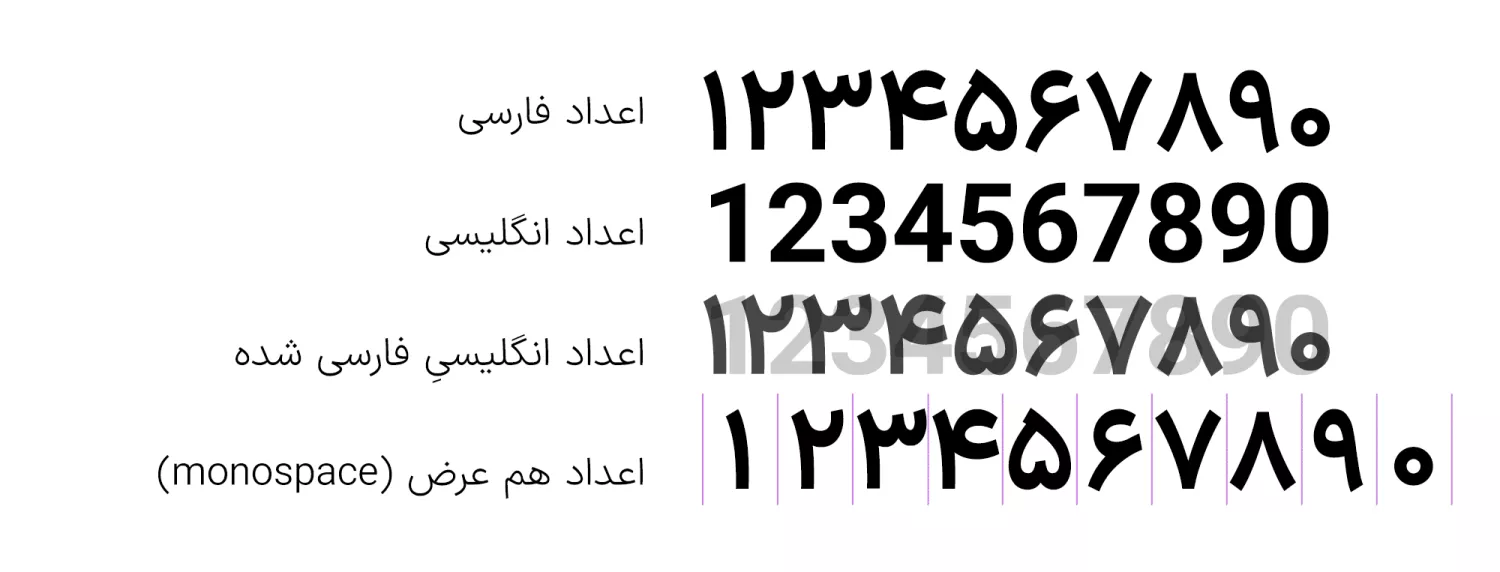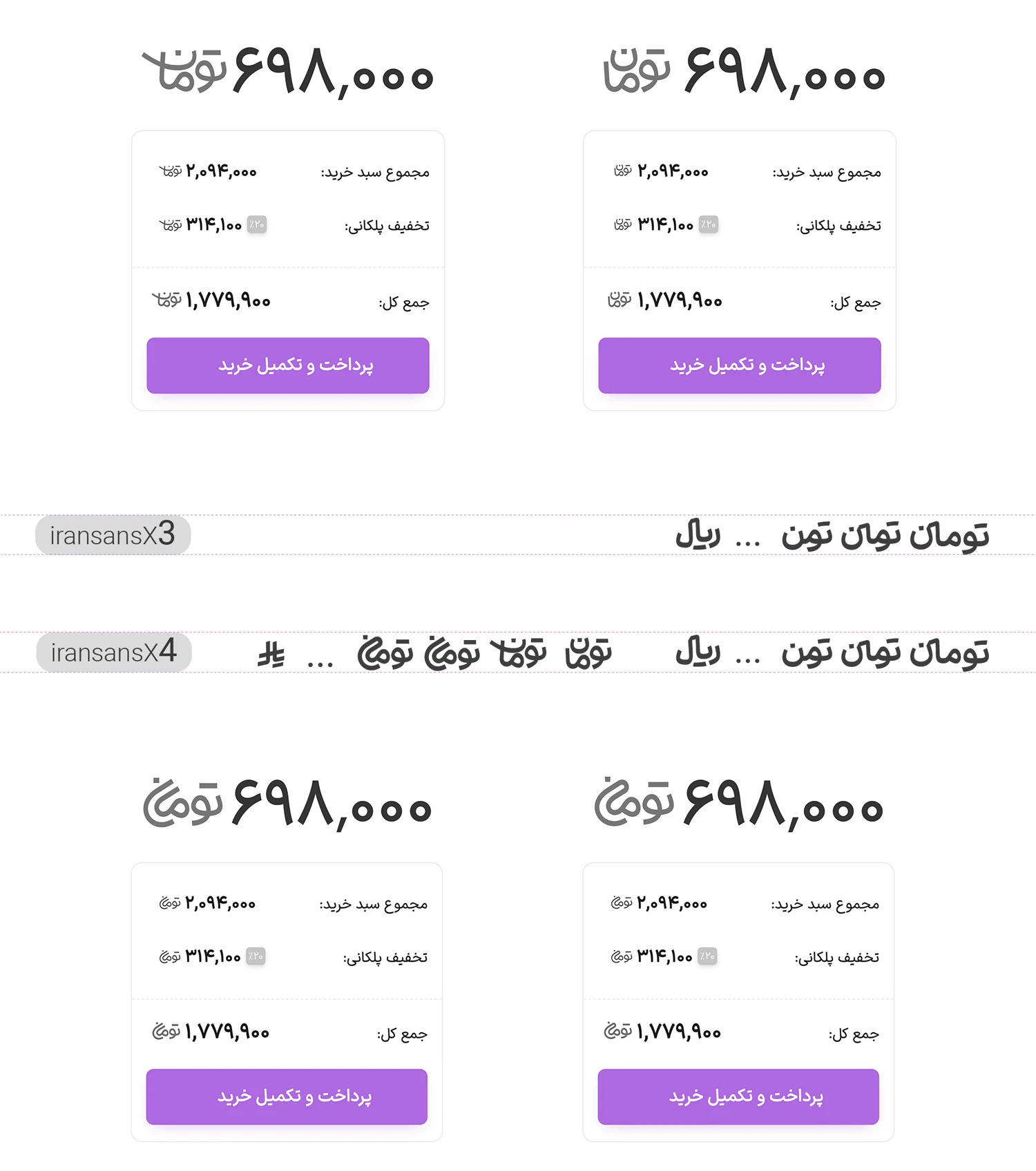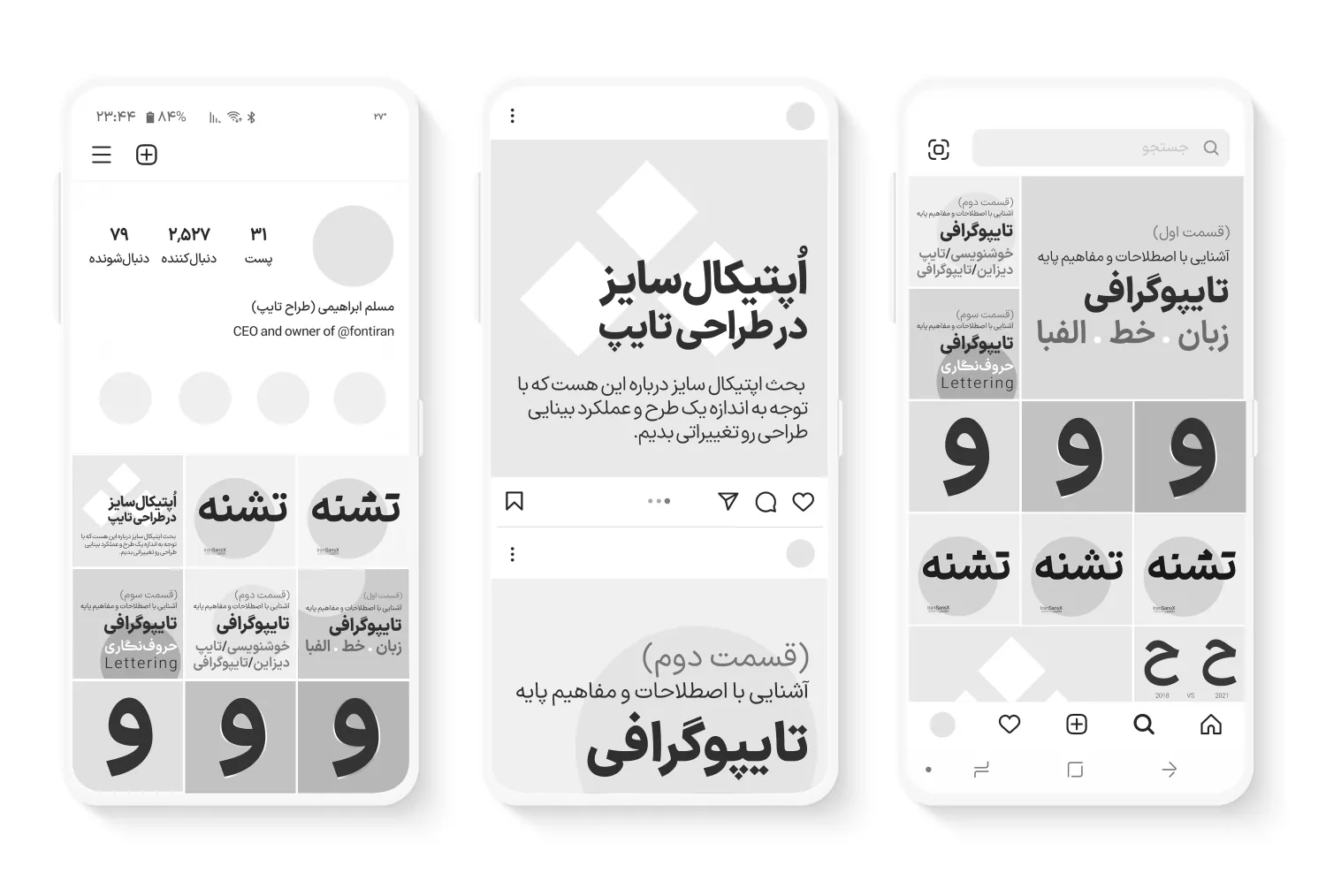
فونت ایران سنس (IranSans)
فونت ایران سنس (به انگلیسی: IranSans) که البته با نامهای ایران سانس و ایرانسنس ایکس نیز شناخته میشود، جزو بهترین فونتهای فارسی است که بیش از ۱۰ سال از زمان ساخت آن میگذرد. این فونت در دسته فونتهای متن، مناسب عناوین، طراحی رابط کاربری و تبلیغات قرار دارد که با توجه به پشتیبانی از ۱۱ وزن مختلف و دارای امکانات خاصی که در برخی از فونتها نظیر ندارد، مورد توجه قرار گرفته است.
مسلم ابراهیمی این قلم را طراحی کرده است که از فونتهای سنس الهام گرفته شده است؛ اما ریشه در خط نسخ فارسی دارد. ضمن اینکه دارای طراحی مدرن و مینیمال است، کاملا نرم و دوستانه بهنظر میرسد و از نظر خوانایی نیز بسیار مناسب است.
در ادامه این نوشته از سایت فونتچی به نقد و بررسی کامل فونت ایران سنس میپردازیم و شما را با امکانات برترین فونت وب فارسی آشنا خواهیم کرد. فونتی با ساختارهای خارق العاده که طیف وسیعی از نیازها را در هر زمینهای برآورده خواهد کرد.
فونت ایران سنس جزو محبوبترین فونتهای فارسی است که در وب مورد استفاده قرار میگیرد و سایتها و مجموعههای بسیار بزرگی از این فونت به تنهایی یا اینکه در ترکیب با سایر فونتها استفاده میکنند.
طبق آمار هرسالهای که توسط برخی سایتها و همچنین وبسایت مرجع این فونت صورت میگیرد، این فونت بیشترین سهم را همچنان از سال ۱۳۹۲ به خود اختصاص داده و در حال یکهتازی است.
سبک طراحی و وزن فونت ایران سنس X
فونت ایران سنس X بر اساس خط سنس طراحی شده است که در آن حروف دارای زوایای نرم و منحنیهای زیادی در دندانهها بوده و خطوط قائم نیز تا حدودی دارای یک زاویه نسبتا منحنی شکل هستند. این فونت از سال ۱۳۹۲ بارها آپدیت شده و ضمن افزودن وزنهای بیشتر، نسخه وریبل و امکانات متعددی به آن افزوده شده است.
پشتیبانی از ۶ زبان مختلف
فونت فارسی ایران سنس محدود به زبان فارسی نبوده و یکی از فونتهای چند زبانه با توجه به پشتیبانی رسمخط زبانهای خاورمیانهای از زبان فارسی است. این فونت از زبانهای عربی، کردی، اردو، ترکی و انگلیسی پشتیبانی کاملی دارد که جدای از حروف شامل اعراب، کاراکترها، سمبلها و طرههای تزئینی هستند.
در زبان عربی که برخی حروف مثل «ک، ی، ه، ؤ، ئ» دارای تایپ متفاوتی نسبت به زبان فارسی هستند، یا در زبانهای کردی و اردو که از طرههای تزئینی و ساختار متفاوت در نوشتن برخی حروف استفاده میشود این فونت پشتیبانی کاملی دارد.
در زبانهای لاتین نیز همین شیوه پیادهسازی شده است. مثلا در زبانهای ترکی استانبولی و فرانسوی که برخی حروف مثل «ı, ğ, ç, ü» دارای نقطه بوده یا شکل متفاوتتری دارند پیادهسازی شده است.
به همین ترتیب کلیه کاراکترها شامل اعراب و اعداد نیز متناسب با هر زبان در این فونت پیاده سازی است که میتوان جدای از اینکه آن را جزو اولین فونت مرسوم وب فارسی دستهبندی کرد، جزو کاملترین فونت فارسی نیز قرار داد که شامل وزنها و ساختارهای متفاوتی از نظر استایل قلم است.
وریبل فونت ایران سنس با تغییر وزن و نقاط
ویژگی دیگر فونت ایران سنس پشتیبانی از حالت وریبل فونت یا همان فونت متغیر است که به عنوان دومین فونت فارسی ایرانی، بعد از فونت دانا به این ویژگی مجهز شد. در نسخه وریبل فونت ایران سنس قادر هستید بهجای استفاده از ۱۱ وزن مختلف، نقطهگذاری فونت در چند سبک مختلف و همچنین تایپ اعداد فارسی و گلیفهای تومان و ریال، صرفا از یک فایل فونت استفاده کنید.
در فونت متغیر ایرانسنس X دو متغیر Weight و Dots در نظر گرفته شده که به ترتیب برای تغییر وزن حروف و تغییر نقطه گذاری مورد استفاده قرار میگیرند.
مشابه تصویر بالا با استفاده از متغیر Weight امکان تغییر وزن فونت را بین بازه ۱۰۰ که برای وزن Thin و مقدار ۱۰۰۰ که برای وزن Heavy است را در اختیار دارید.
به همین ترتیب میتوانید با تنظیم ۰ تا ۸ از ۸ حالت مختلف نقطه گذاری مشابه تصویر بالا در فونت ایران سنس متغیر استفاده کنید. این نقاط در سبکهای مختلف دایرهای، مربعی، چسبان، هندسی و مورب قابل استفاده هستند.
اعداد فارسی و عربی فونت ایران سانس ایکس
ویژگی دیگر فونت ایران پشتیبانی از تایپ اعداد فارسی و عربی متناسب با هر زبان است. در زبان عربی که اعداد «۴۵۶» دارای ساختار متفاوتی نسبت به فارسی «۴۵۶» هستند در این فونت پیاده سازی شده است.
علاوه بر این فونت برای همه زبانهای فارسی، عربی، انگلیسی و سایر زبانهایی که پشتیبانی میکند امکان تایپ اعداد به صورت مونو اسپیس (MonoSpace) را در اختیارتان قرار میدهد. برای این منظور به تصویر زیر دقت کنید.
همانطور که میبینید، در اعداد برای همه زبانها در ردیف اول و دوم شاهد عرض متفاوت هستیم. مثلا عدد ۳ که نسبت به عدد ۲ دارای یک دندانه بیشتر است، فضای بیشتری را اشغال کرده است؛ به همین ترتیب عدد ۱ کمترین میزان را دارد.
در حالی که در ستون چهارم میبینید که اعداد دارای عرض ثابتی هستند. در ستون سوم نیز همین ویژگی برای دو اعداد فارسی و لاتین مقایسه شده است.
دیگر ویژگی اعداد در فونت ایران سنس ایکس امکان تغییر تراز عمودی است که میتوانید آن را با استفاده از تنظیمات open type نرم افزار گرافیکی در دو سطح خط کرسی تغییر دهید تا برای زمانهایی که از کلمات در کنار حروف استفاده میکنید، خط کرسی هماهنگی داشته باشند.
تمامی قابلیتهای فوق که برای اعداد و همچنین استفاده از گلیفهای واحد پولی ایران وجود دارد، در نسخه وریبل ایران سنس ایکس نیز قابل استفاده هستند که کافی است مطابق فایل راهنمای PDF فونت از آنها استفاده کنید.